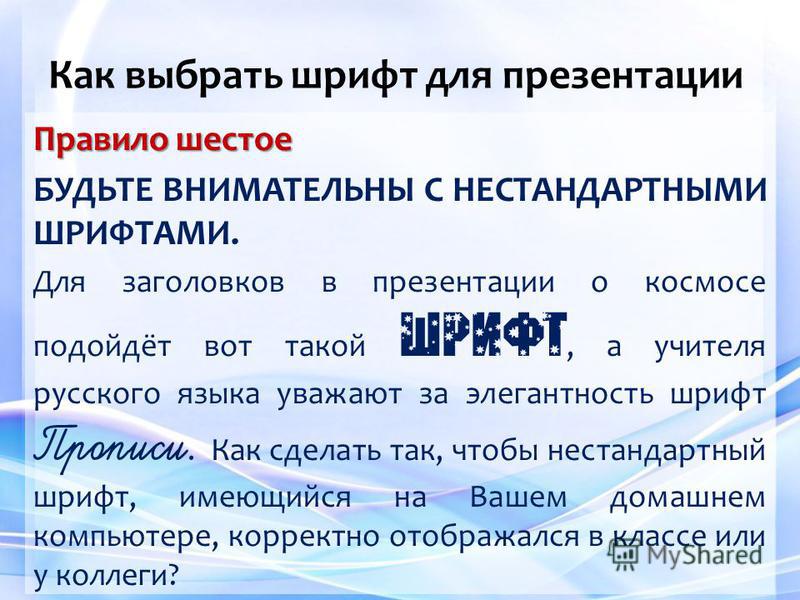
Шрифт
• Выбор величины кегля для набора текста издания
регламентирован.
• ОСТ 29.124-94 «Издания книжные. Общие технические
условия» среди гигиенических требований к
оформлению книжных изданий для взрослого читателя
ограничивает минимальную величину кегля шрифта
основного текста:
— в литературно-художественных изданиях 9 пунктами,
— в научно-популярных, научных, справочных,
нормативных и проч. изданиях для взрослых читателей
— 8 п. В энциклопедиях и словарях допускается
использование и более мелкого — 7 п. — шрифта. В то
же время, при печати на газетной бумаге, обладающей
пониженной белизной и, соответственно, контрастом,
минимально допустимые кегли шрифтов основного
текста увеличиваются на 1 п.
• В издательской практике в книгах для взрослого читателя
широко применяется шрифт 10 кегля. Он достаточно хорошо
читается на расстоянии 30-35 см. Применяют шрифт 9 кегля с
увеличением на 1 пункт интерлиньяжа (такой шрифт
обозначается как 9/10). Увеличенный интерлиньяж повышает
удобочитаемость и красоту набора. Рекомендуется
использовать увеличенный интерлиньяж в изданиях при
наборе шрифтом мелких кеглей.
• В справочных изданиях возможно применять шрифт 8 и 7 кегля
– для справочных изданий важна компактность (в справочных
изданиях за один приём читается сравнительно небольшое
количество текста, поэтому малый кегль не утомляет зрение).
Шрифт 8 кегля подходит и для сборников стихов небольших
форматов.
• Шрифт 6 кегля очень мелок, читается хуже и поэтому
применяется лишь для таких книжных изданий, где необходима
особая компактность, например, для словарей-малюток, или –
для миниатюрных памятных и подарочных изданий.
Гарнитура – комплект шрифтов одного рисунка, но разных размеров
(кеглей) и начертаний. Каждая гарнитура имеет свое название
(«Школьная», «Академическая» и др.). Многие гарнитуры названы по
имени их создателей – художников: гарнитура Лазурского, Кудряшевская
энциклопедическая, Кузаняна, Рерберга, Банниковская и др.
При подготовке художественной литературы издательства чаще
используют гарнитуры «Антиква», «Баскервилль», «Литературная»,
«Таймс»; научно-технической, справочной и учебной литературы –
«Г(Х)ельветика», «Прагматика», «Таймс»; энциклопедических изданий –
«Кудряшевская», «Литературная», «Таймс».
Гарнитура для детских изданий и учебной литературы для
общеобразовательной школы выбирается в соответствии с ОСТом 29.1272002 и действующими СанПиНами. Рекомендуемые гарнитуры –
«Букварная» (рубл), «Азбука», «Журнальная рубленная», «Школьная» (с
засечками).
Для изданий для взрослых малого кегля (не более 8) соответсвующий ОСТ
(29.124-94) рекомендует использовать равноконтрастные или
незначительной контрастности гарнитуры типа Литературная, Балтика,
Гельветика, Журнальная рубленая, Новая журнальная,
Энциклопедическая, Нева, Академическая, Журнальная, Школьная и др.
Требования к шрифтам
• Издание в целом должно отвечать ряду требований
гигиенического, эстетического, экономического,
технического, технологического и производственного
характера.
• С эстетической точки зрения шрифт должен быть
красивым.
• Экономичность шрифта характеризуется его ёмкостью и
определяется тем, какое количество печатных знаков
можно разместить в строке, в полосе, в изданиях равных
форматов. Применение экономичных шрифтов не только
существенно уменьшает расход бумаги, но и приводит к
уменьшению объема (а следовательно, и стоимости)
многих типографских работ, необходимых для выпуска
данного издания. И все же экономичность шрифта нужна
и полезна только при условии, что она достигается не за
счет удобочитаемости.
Производственно-технические и технологические требования к
шрифтам:
В процессе печатания рисунок шрифта в большей или меньшей степени
деформируется. Степень деформации шрифта зависит от характера его
рисунка, от вида печати (высокая, глубокая, плоская (офсетная)), от качества
бумаги (мелованная, глазированная, газетная).
Экспериментально установлено, что при печатании наиболее точно
воспроизводятся шрифты с умеренной контрастностью (или вовсе лишенные
контрастности), с короткими засечками, с достаточно широкими
внутрибуквенными просветами. Наоборот, шрифты с резкой контрастностью,
длинными, почти сливающимися засечками и узкими внутрибуквенными
просветами искажаются сильнее.
Наименьшее искажение получается при печатании способом высокой
печати непосредственно со шрифта (с оригинальной формы) и способом
офсетной печати по современной технологии (меньше промежуточных
этапов). Очень тонкие засечки плохо воспроизводятся при офсетной печати.
Тонкие штрихи «съедаются», текст выходит «слепым». Для глубокой печати
резко контрастные шрифты совсем не подходят.
Тип используемой для печати бумаги. Так, на газетной бумаге, например,
Jost
Jost — хорошая бесплатная альтернатива классической игре Futura. Вдохновленный традиционным шрифтом без засечек, Jost является модным шрифтом цифровой эпохи. Это хороший вариант сделать вашу презентацию более современной, не слишком дерзкой или небрежной.